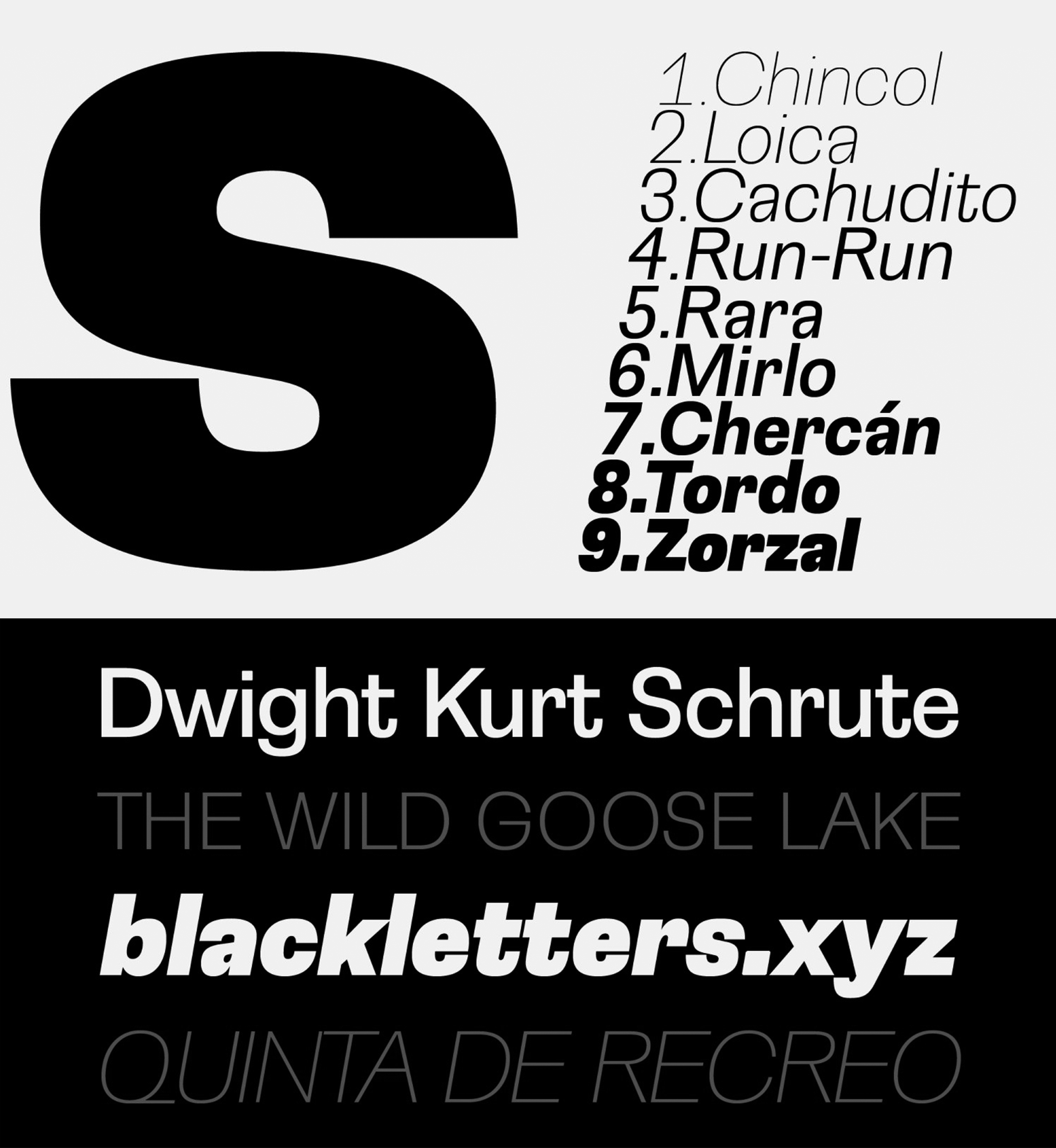
| Descripción | Loica Sans es una nueva (sí, una más) interpretación del estilo tipográfico neogrotesco con una sutil actitud exuberante. Esta versión busca dotar a un estilo que se caracteriza por ser transparente y neutral de un aspecto sofisticado mediante el dibujo de glifos con trazos sutilmente exuberantes. La idea general es subvertir la supuesta neutralidad de este estilo, que, como muchos otros en la tipografía, está lleno de sutilezas y detalles. Disponible como fuente variable, OpenType, TrueType y WebFonts. |